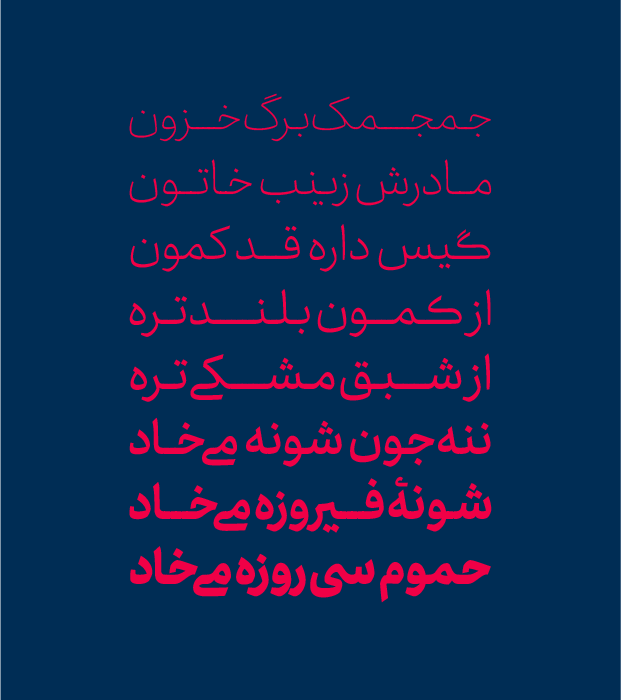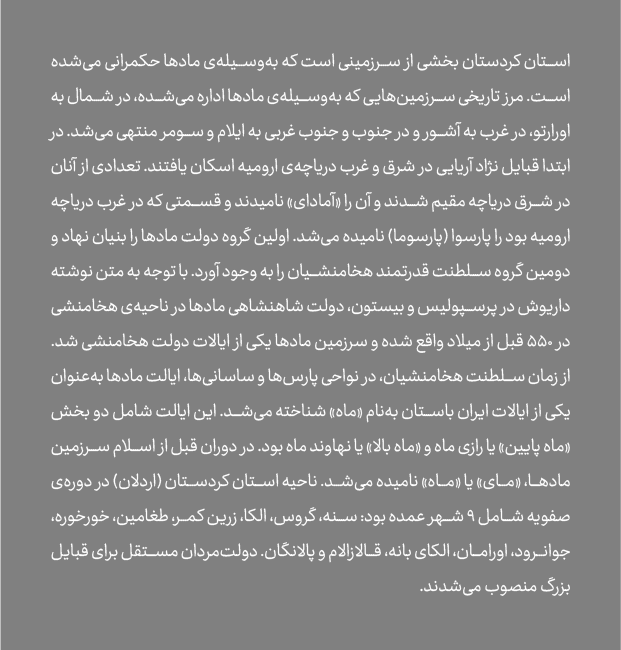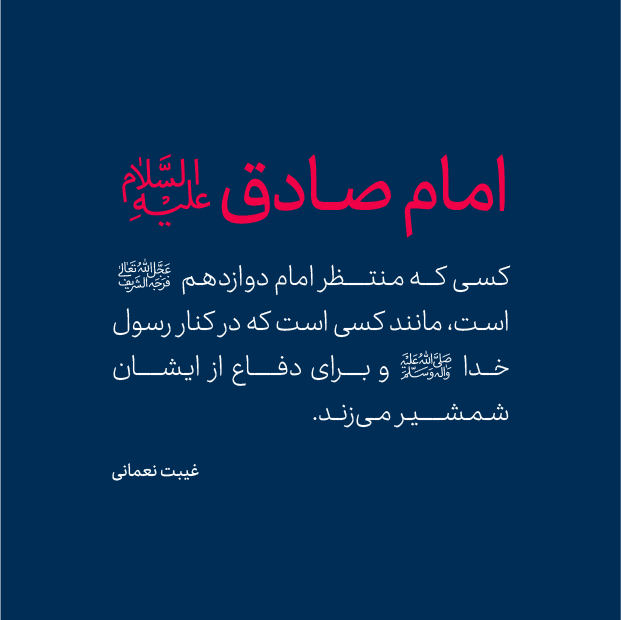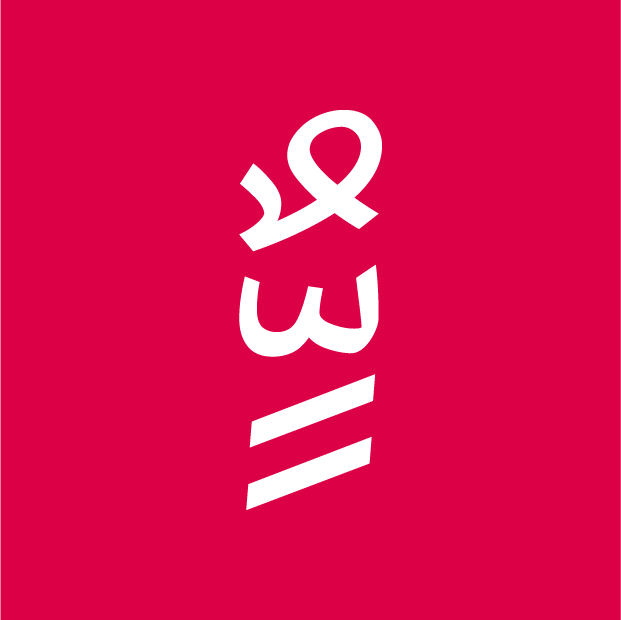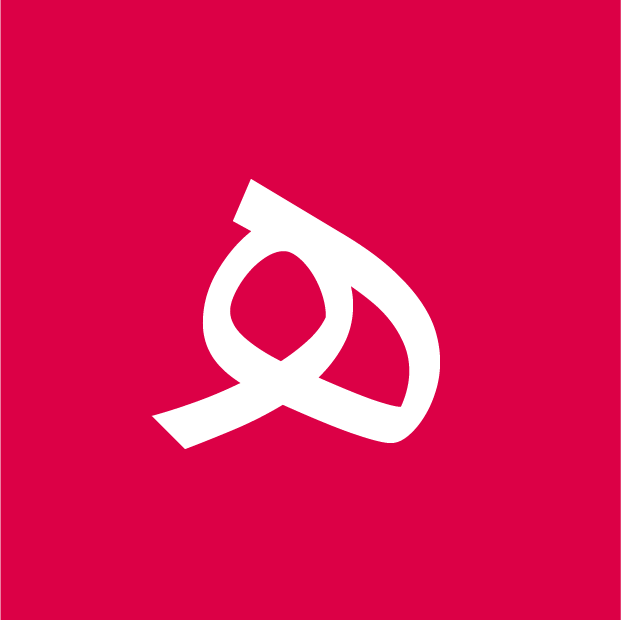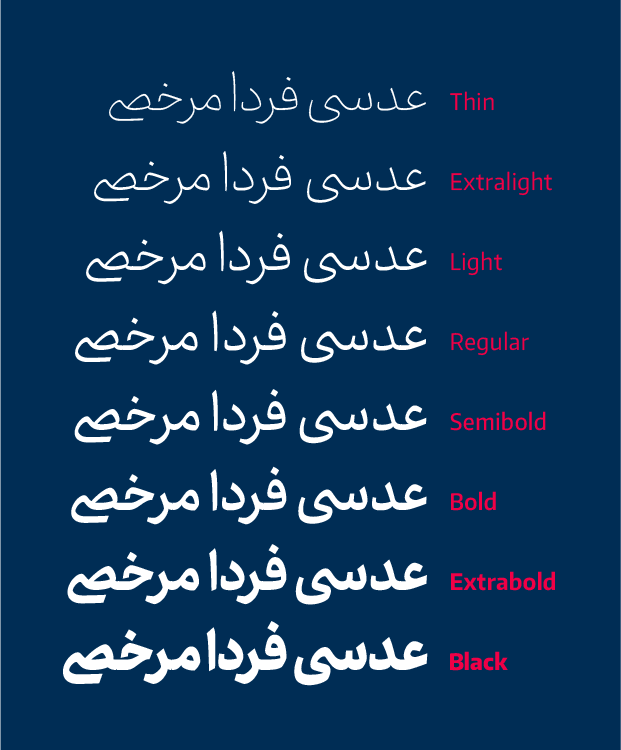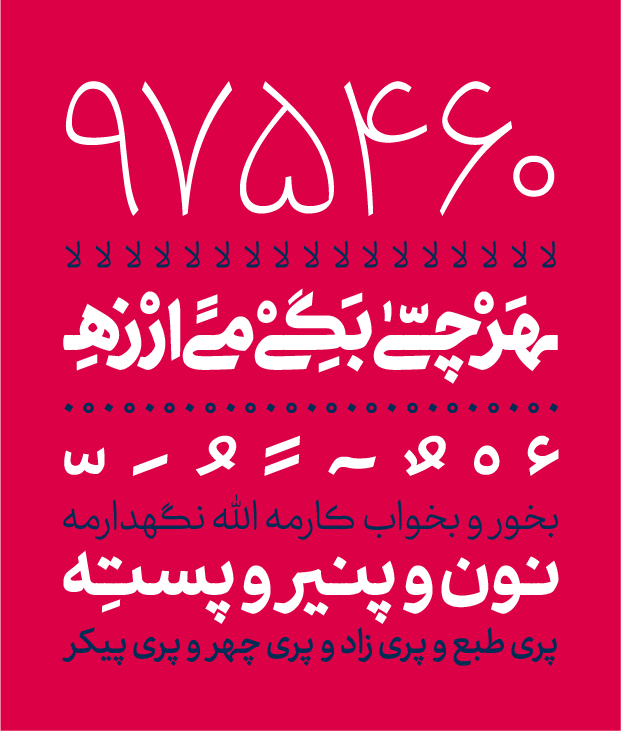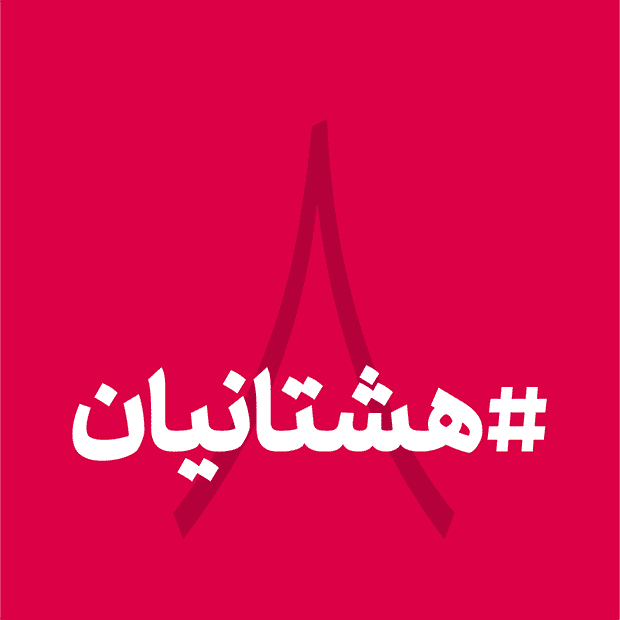
قلم نیان
کاری از افسانه سالک و رضا بختیاری فرد
درباره قلم نیان
در طراحی قلم نیان، تمرکز اصلی بر روی افزایش خوانایی آن قرار داده شده است. این قلم به‌گونه‌ای طراحی شده که بتواند کمبود قلم‌های جدید و مناسب برای نوشته‌های عمومی را به‌خوبی جبران کند. در فرآیند طراحی، سعی شده است تا ارتباط با گذشته و ریشه‌های خط فارسی حفظ شود؛ در عین حال که ظاهری مدرن و امروزی دارد. هدف این طراحی، ایجاد تعادل بین سنت و نوآوری است تا کاربران بتوانند از آن در متن‌های متنوع و مختلف استفاده کنند.
قلم نیان به‌عنوان یک قلم محکم با استخوان‌بندی آشکار شناخته می‌شود. این ویژگی، فرم‌های مسطح‌تر و مفصل‌های بیشتری را در حروف به وجود آورده که به زیبایی و خوانایی آن می‌افزاید. نیان دارای ۸ وزن مختلف است که هر یک کاربردهای خاص خود را دارد. وزن‌های پایه این قلم به‌طور ویژه برای استفاده در نوشته‌های بلند، مانند کتاب‌ها و مجلات طراحی شده‌اند، و به‌علاوه، وزن‌های ضخیم‌تر این قلم برای استفاده در آثار گرافیکی و تبلیغاتی به‌طرز مؤثری کارایی دارند.
کاراکترهای لاتین به‌کار رفته در این قلم، Encode Sans نام دارند و تحت مجوز OFL منتشر شده‌اند. این انتخاب، به‌دلیل همخوانی و تناسبی است که بین کاراکترهای لاتین و فارسی وجود دارد و استفاده از این قلم را در پروژه‌های بین‌المللی تسهیل می‌کند. همچنین، قلم نیان از زبان‌های مختلفی از جمله فارسی، عربی، اردو، کوردی و جاوی پشتیبانی می‌کند.
طراحی قلم نیان از سال ۹۰ آغاز شد و در طول زمان، تغییرات و بهبودهای متعددی را پشت سر گذاشت تا نهایتاً در سال ۹۵ به یک مرحله تکامل برسد. پس از آن، طراحی و تکمیل وزن‌های مختلف این قلم طی دو سال انجام شد تا در نهایت محصولی کامل و متناسب با نیازهای کاربران ارائه شود. این قلم نه تنها یک ابزار نوشتاری است، بلکه نمادی از تلاش در راستای ارتقای کیفیت و زیبایی در حوزه تایپوگرافی مدرن محسوب می‌شود.